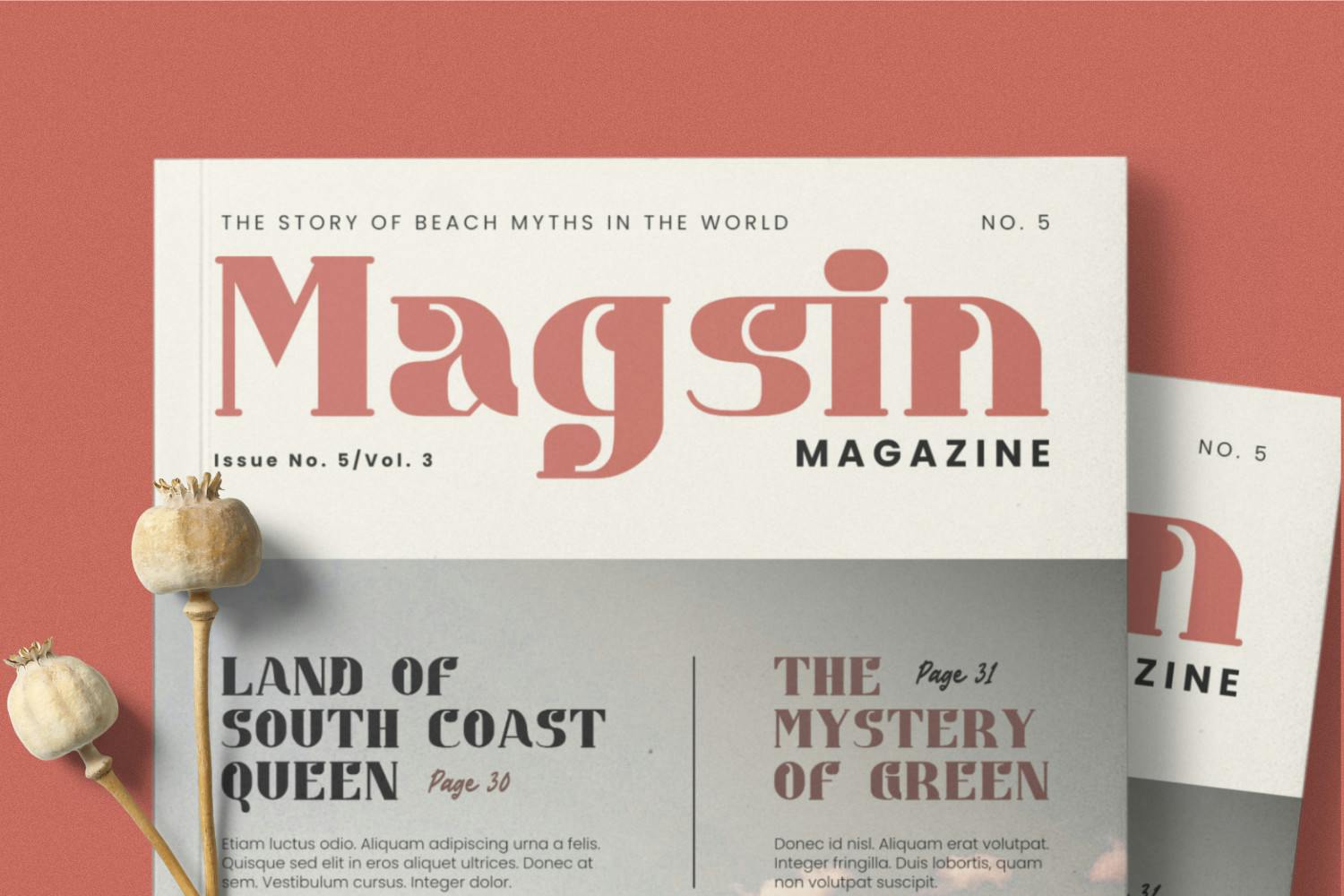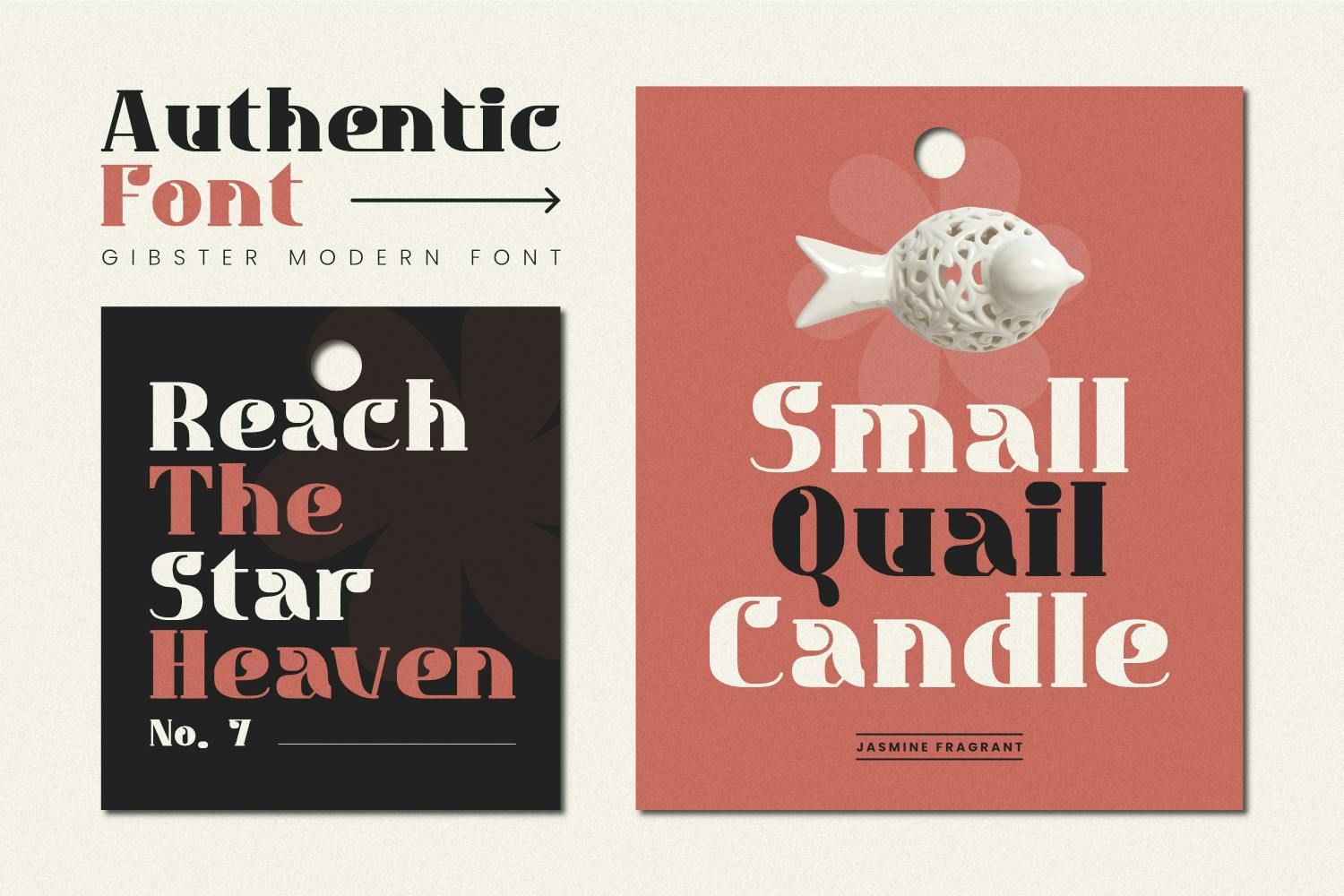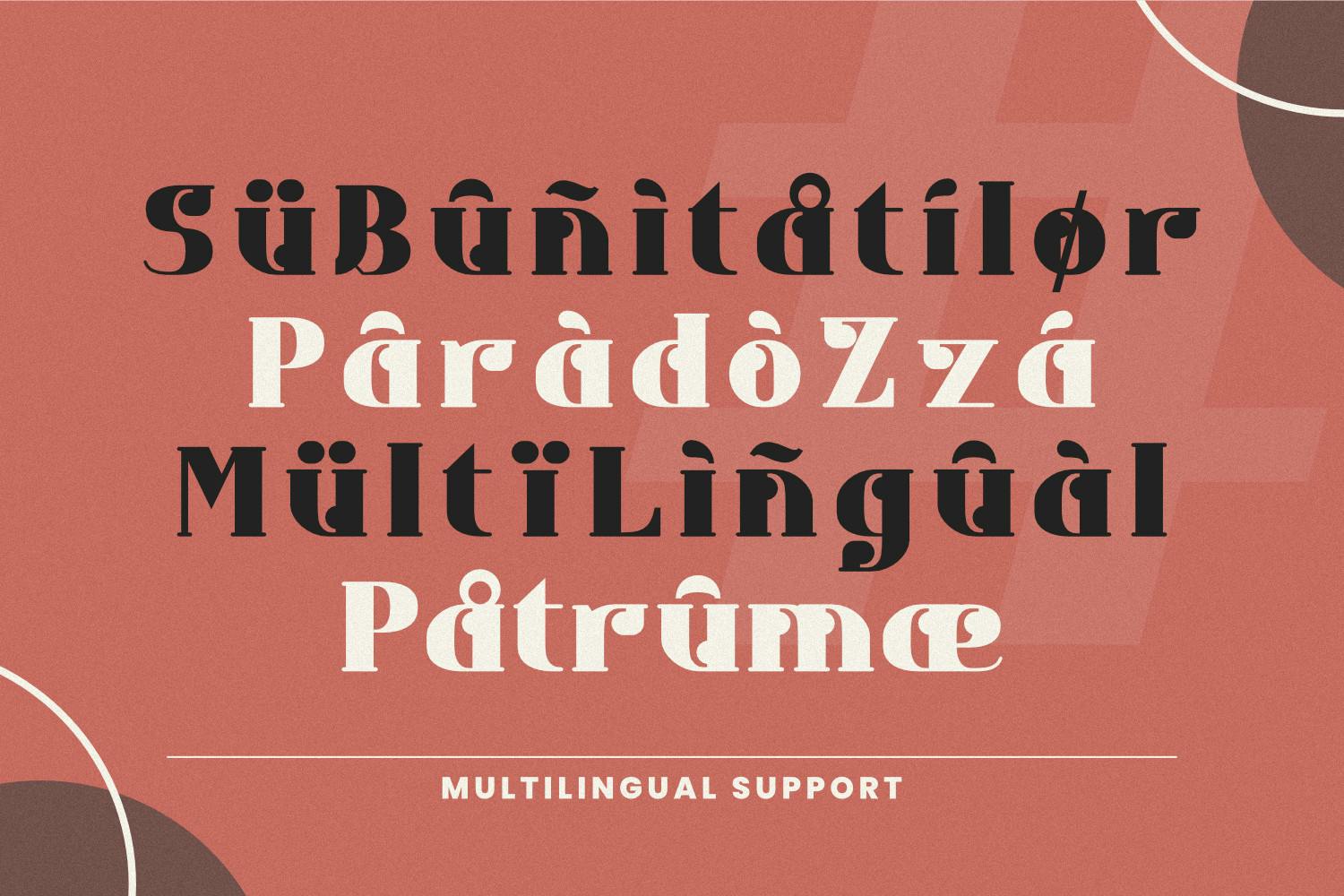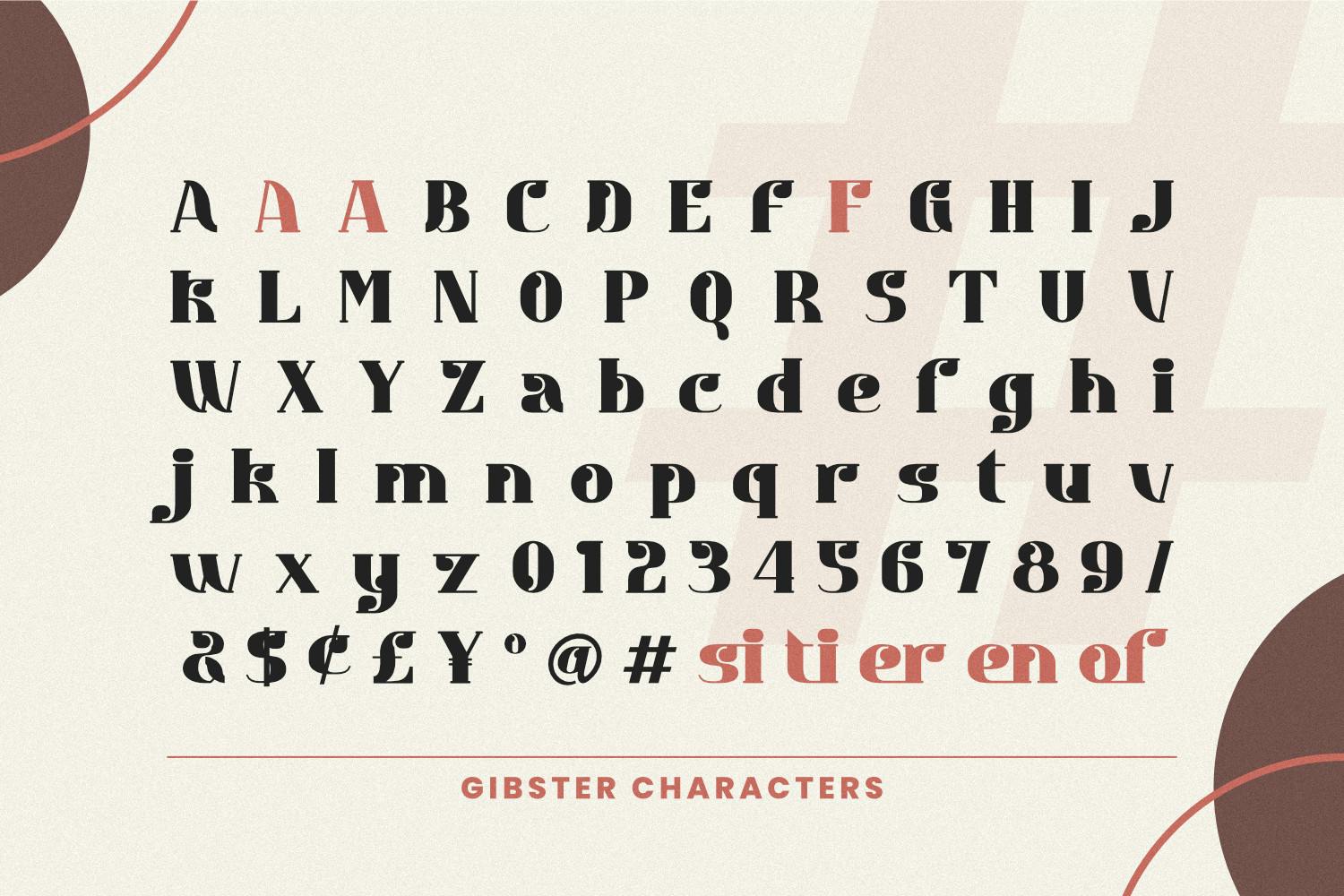
محصول فونت Gibster برای بسیاری از پروژههای شما مانند طراحی لوگو و برندینگ، عکاسی، دعوتنامهها، واترمارکها، تبلیغات، طراحی محصولات، لوازمالتحریر، طراحی عروسی، برچسبها، بستهبندی محصولات، رویدادهای خاص و بسیاری موارد دیگر مناسب است.